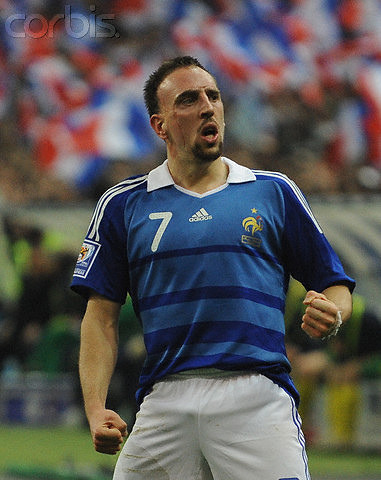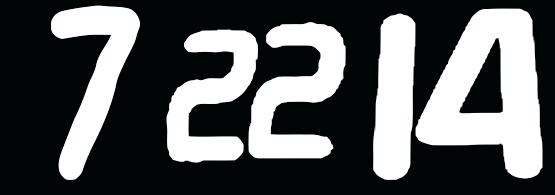
Kennt jemand die Font dieser Zahlen oder eine ähnliche
kann mir jemand sagen welche Schriftart die unten aufgeführte ist? Über ähnliche Vorschläge freue ich mich auch.
Die Zahlen sind normalerweise glatt ist leider durch die Vergrößerung so gekommen.
Fußballtrikots? Wenn ja, welche Mannschaft?
Über ähnliche Vorschläge freue ich mich auch.
Je nachdem, wie ähnlich es sein muss, könntest du evtl. hier fündig werden. Die Komika Text hat z.B. die oben geschlossene 4; viele Schriften haben die 1 und 7 in den gesuchten Formen. Das größte Problem dürfte die »rechtwinklige« 2 sein, wenn du eine solche denn benötigst.
Vielleicht findet sich ja ein Fußballfan … müsste das 2009er Trikot der französischen Nationalmannschaft sein.
Ich weiß nur, dass die Sportkleidungs-Hersteller extra dafür eine Typografie-Abteilung haben, welche jeweils für die Kunden neue Ziffen entwickeln, die nie als Font veröffentlicht, aber als Marke registriert werden, um so Markenfälschungen besser verfolgen zu können. Die Schrift liegt dann ausschließlich Hausintern vor, und die Trikots werden dann fertig beflockt geliefert. Zumindest gilt dies für die Vereine der oberen Ligen, sowie für Nationalmannschaften. Für die unteren Klassen gibt es natürlich Zahlensätze in Standardformen, die nicht geschützt sind, und die auch oft aus Flockfolie nach irgend einem Font geschitten werden. Aber von SC Klötersdorf wird auch kaum jemand das Trikot fälschen.
Catfonts leider stimmt deine Antwort nicht ganz, z.B. hat der BVB eine Standart Schrift die du ganz normal kaufen kannst, es gibt aber da muss ich dir Recht geben einige Vereine die es so machen wie du schon sagtest.
Nun ja, die normale Schriftart auf der BVB-Seite „riecht“ irgendwie nach FF DIN oder DIN 1451, allerdings ist die Tikot-Schrift und die Ziffern doch so speziell, dass ich mir die Downloadbarkeit kaum denken kann, aber ich lass mich gern eines besseren belehren.
Allerdings ist der BVB ja auch mittlerweile eine Größe, aber eben bei weitem mit einer anderen Einstellung, wie die „Großkopferten“ in Bayern, von daher kann ich mir schon vorstellen, das die mit kreativen Fans Mitleid haben.
Und damit ist man dann auch wieder bei den Ausrüster-Spezialentwicklungen, welche das Haus des Ausrüsters nur in fertiger Form verlassen - was natürlich die Fälscher in Fernost nicht abhält, das nach Fotos neu zu zeichnen. Denen ist es ja egal, ob der Besteller der Fälschung dann in den Stadien mit dem billig-Trikot steht, oder ob dieses vom Zoll eingezogen und vernichtet wird, eigentlich ist denen letzteres fast noch lieber, da so mancher dann noch einmal einen Ersatz bestellt...
Auch wenn dann diese Schrift nicht für einen einzelnen Verein als Marke geschützt ist, ist die dann zumeist vom jeweiligen Sportbekleidungs-Hersteller (zumeist zusammen mit der FIFA als Marke registriert, und somit auch wieder nicht als Font zu haben.
Eine Schrift (also die Form, nicht den Namen) als Marke schützen? Hat das wirklich schon jemand gemacht? Da würden mich Beispiele interessieren.
Die ursprünglich gesuchte ist übrigens mit nur geringen Abweichungen bei Trikotherstellern verfügbar: